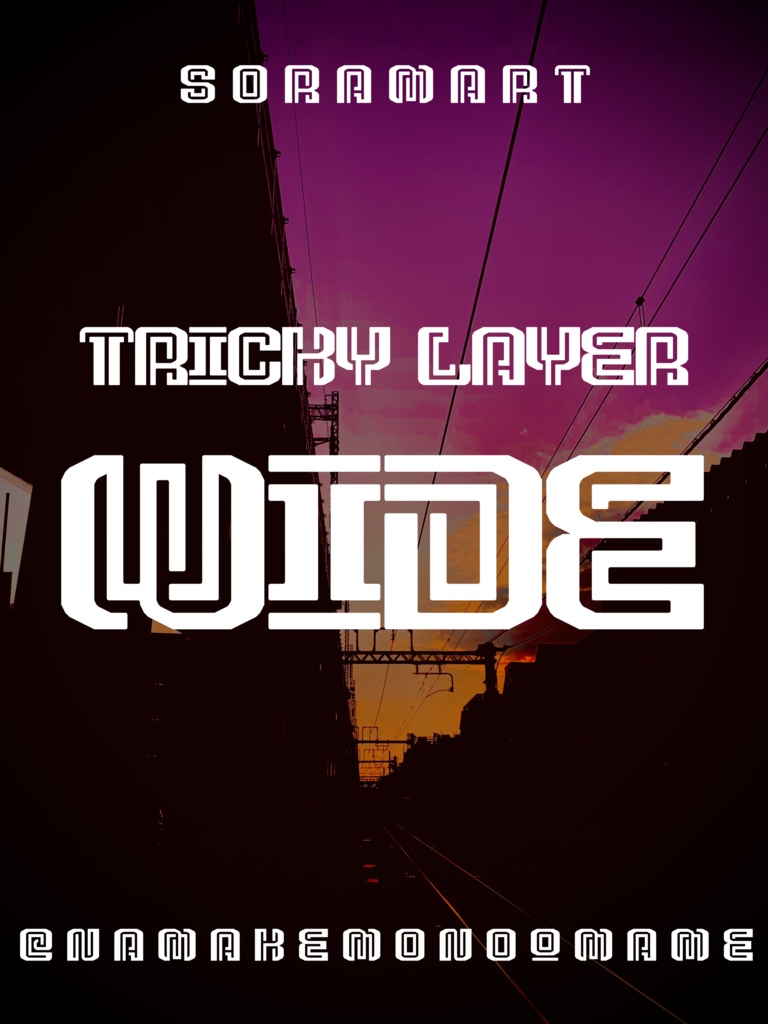
そらマートフォントデータ”Tricky Layer Wide”Digital2,500 JPYAdd to CartBuy a GiftAbout Gift二層構造になった2つのラインが入り組むフォントの幅広アレンジ版 "Tricky Layer Wide" です。 「TrueTypeフォントファイル」という形式です。 ダウンロードした後、Zipファイル内のデータをインストールしてお使いください。 このフォントは商用利用可となっております。 お客様の制作・創作活動のお役に立てれば幸いです。 ※使用上の注意事項などは、添付のReadmeをお読みください。そらマートVisit FANBOX!Fontsフォントデータ”Longtail Sans Serif Slashed”そらマート2,500 JPYFontsフォントデータ”Longtail Sans Serif Bold”そらマート0 JPYFontsフォントデータ”Longtail Sans Serif”そらマート0 JPYFontsフォントデータ”Pretty Commando”そらマート2,500 JPYFontsフォントデータ”Abyss Dive Punk Retro”そらマート2,500 JPYFontsフォントデータ”Abyss Dive Punk Wide”そらマート2,500 JPYFontsフォントデータ”Abyss Dive Punk”そらマート2,500 JPYFontsフォントデータ”Emerald Sphere Sprite”そらマート2,500 JPYFontsフォントデータ”Emerald Sphere Long”そらマート2,500 JPYFontsフォントデータ”Emerald Sphere”そらマート2,500 JPYFontsフォントデータ”Monolith Glitch”そらマート2,500 JPYFontsフォントデータ”Monolith Formula”そらマート2,500 JPYFontsフォントデータ”Rolling Cute”そらマート2,500 JPYFontsフォントデータ”Tricky Wire Merge”そらマート2,500 JPYFontsフォントデータ”Tricky Layer”そらマート2,500 JPYFontsフォントデータ”Popcorn Tab Plasma”そらマート2,500 JPYFontsフォントデータ”Popcorn Tab Heavy”そらマート2,500 JPYFontsフォントデータ”Popcorn Tab”そらマート2,500 JPYFontsフォントデータ”Tetra Pixel Dash”そらマート2,500 JPYFontsフォントデータ”Tetra Pixel Fluid”そらマート2,500 JPYSee More